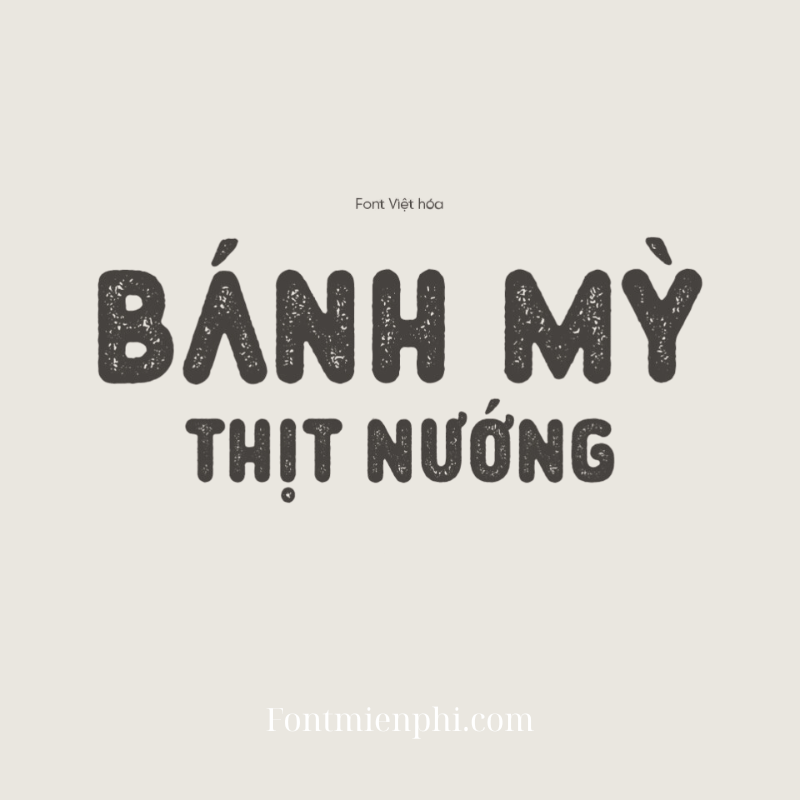
Font Việt hóa 1FTV VIP Plopin Rough
Font Việt Hóa 1FTV VIP Plopin Rough – Phong Cách Độc Đáo Cho Thiết Kế Sáng Tạo
Giới Thiệu
Font Việt hóa 1FTV VIP Plopin Rough là bộ font chữ nghệ thuật độc đáo, được thiết kế dành riêng cho ngôn ngữ Tiếng Việt. Với nét vẽ thô ráp nhưng đầy cá tính, font chữ này phù hợp cho các dự án thiết kế sáng tạo, poster, logo, hoặc ấn phẩm truyền thông ấn tượng.
Đặc Điểm Nổi Bật
• Phong cách thô ráp, nghệ thuật: Plopin Rough mang đến nét chữ không đồng đều, tạo cảm giác hand-drawn độc đáo.
• Hỗ trợ Tiếng Việt đầy đủ: Font bao phủ toàn bộ bảng mã Unicode, đảm bảo hiển thị rõ ràng mọi ký tự có dấu.
• Đa dạng ứng dụng: Phù hợp cho thiết kế đồ họa, in ấn, quảng cáo, hoặc làm font chữ nổi bật trên mạng xã hội.
Lợi Ích Khi Sử Dụng
• Tạo điểm nhấn mạnh mẽ cho thiết kế nhờ phong cách phá cách.
• Dễ dàng sử dụng với bộ ký tự Tiếng Việt hoàn chỉnh.
• Tăng tính thẩm mỹ và sự khác biệt cho mọi dự án.
Kết Luận
Font Việt hóa 1FTV VIP Plopin Rough là lựa chọn tuyệt vời cho designer muốn tạo ra sản phẩm đậm chất nghệ thuật. Nếu bạn đang tìm kiếm một font chữ cá tính, phá cách và tối ưu cho Tiếng Việt, đây chính là giải pháp hoàn hảo.